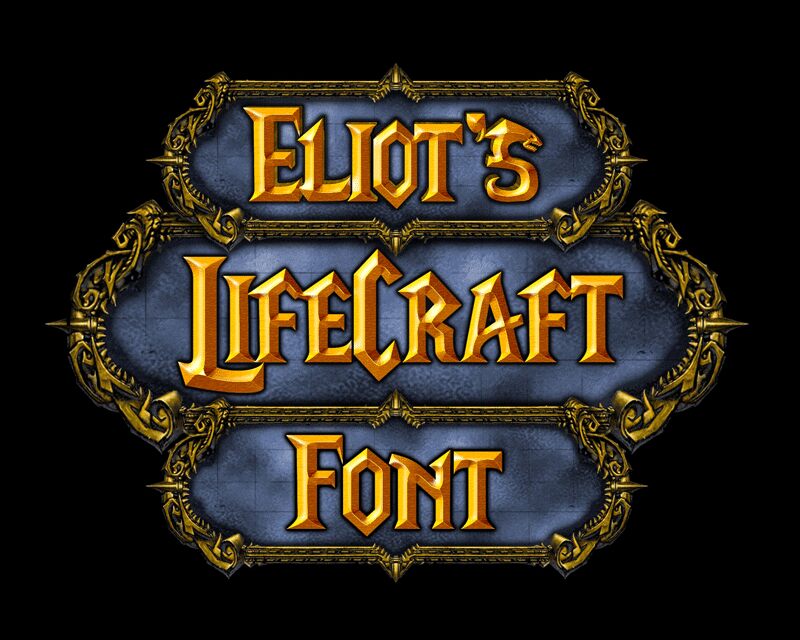
LifeCraft ist eine kostenlose, moderne Blackletter-Schrift (Versalien), die auf wuchtigen Strichen, messerscharfen Winkeln und markanten Diamantspitzen aufbaut. Ihr mittelalterlicher Charakter wird durch breite, schwungvolle Füße und geometrische Schnitte geschärft, was den Buchstaben eine kraftvolle, emblematische Präsenz verleiht, ohne den handgefertigten Charme zu verlieren.
Nutzen Sie diese kostenlose Schrift für Titel von Fantasy-Spielen, Albumcover von Metal-Bands, Plakate für Mittelaltermärkte, das Branding von Tattoo-Studios oder heraldische Merchandise-Artikel. Sie eignet sich besonders gut für kurze Überschriften, Titelkarten und Monogramme, bei denen die spitzen Versalien und die dramatischen unteren Schwünge genügend Raum haben, um die Komposition zu bestimmen.